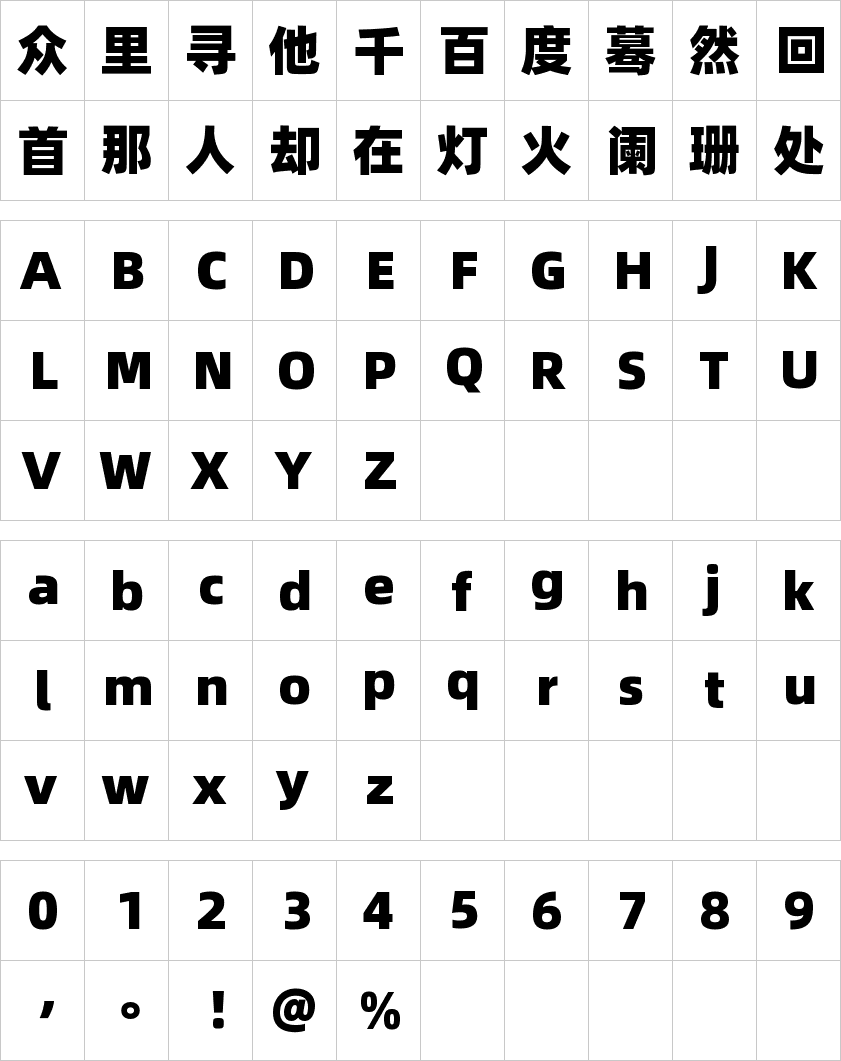
阿里巴巴普惠体-Heavy
阿里巴巴普惠体是阿里巴巴发布的字体,它将开放商业授权给所有个人和商家,让所有用户可以免费使用 。阿里巴巴普惠体1.0收录了11.6万汉子,7205个拉丁字母,覆盖173个语种。中文字体5个字重,西文字体(Alibaba Sans)11个字重,可满足多业务应用场景的组合表现需求。笔画简洁,造型瘦长,重心较高,充分展现了20岁阿里少年的精气神。
2021年5月14日,在2021阿里巴巴设计周现场,阿里巴巴发布“阿里巴巴普惠体2.0”,免费面向全社会开放下载和使用,并承诺在所有平台均可永久免费商用。在原有的1.0版本基础上,“阿里巴巴普惠体2.0”的中文字体优化了部分字体结构、新增4个字重(字体粗细),外文字体新增了泰文和越南文,方便在东南亚经营的中小企业使用。截至目前,字库共囊括222841个字符,覆盖全球175个语种。